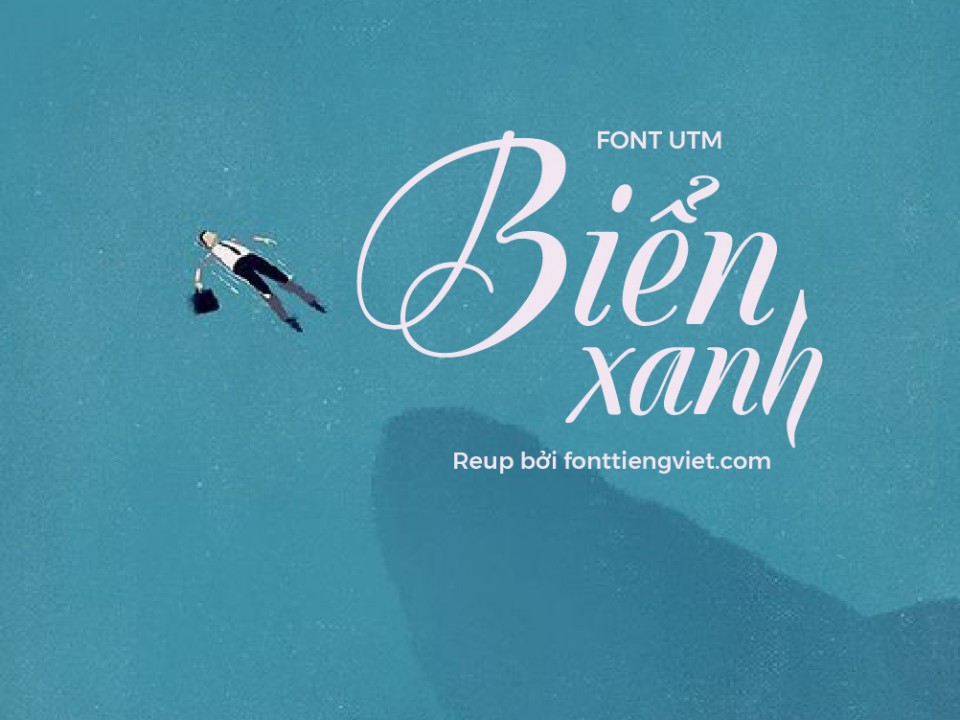
Font việt hóa UTM Silk Script
Giới thiệu về Font việt hóa UTM Silk Script
Trong thế giới đồ họa hiện đại, việc lựa chọn một bộ Font Miễn Phí chất lượng là yếu tố quyết định sự thành công của tác phẩm. Font việt hóa UTM Silk Script là một trong những phông chữ viết tay thanh lịch được yêu thích nhất. Với những đường nét uyển chuyển, mềm mại như dải lụa, bộ font này mang đến vẻ đẹp sang trọng và tinh tế cho mọi bản thiết kế. Đặc biệt, phiên bản này đã được việt hóa hoàn chỉnh giúp người dùng dễ dàng gõ tiếng Việt có dấu mà không lo lỗi hiển thị.
Đặc điểm nổi bật của font chữ
UTM Silk Script sở hữu cấu trúc các ký tự nối liền nhau tạo cảm giác liên tục và tự nhiên. Sự kết hợp giữa nét thanh và nét đậm giúp tổng thể văn bản trở nên sống động, phù hợp cho các chủ đề về giáo dục, thiệp mời hoặc trang trí bìa sách học đường. Với khả năng tương thích cao trên nhiều phần mềm thiết kế như Photoshop hay Canva, đây thực sự là công cụ đắc lực cho các bạn học sinh và giáo viên sáng tạo bài giảng sinh động.
Ứng dụng Font việt hóa UTM Silk Script trong đời sống
Bộ font này cực kỳ đa năng khi ứng dụng vào thực tế. Bạn có thể sử dụng Font việt hóa UTM Silk Script để thiết kế bằng khen, giấy khen cho các kỳ thi cấp trường hoặc trang trí sổ tay cá nhân. Những đường nét nghệ thuật của nó giúp thông điệp truyền tải trở nên gần gũi và giàu cảm xúc hơn. Ngoài ra, phông chữ còn thường xuyên xuất hiện trên các ảnh trích dẫn (quotes) truyền cảm hứng học tập trên mạng xã hội.